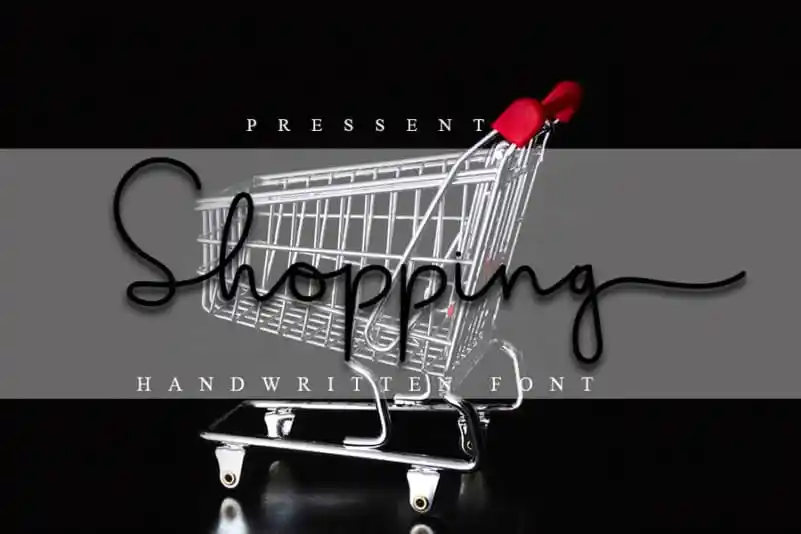
Shopping Script Font – Download Grátis
A Shopping Script Font é uma elegante escolha para quem procura um estilo handwritten contemporâneo e vivaz. Embora mantenha influências tradicionais da escrita aquarelada, essa fonte se destaca pela sua versatilidade em adaptar-se de maneira suave a diversos formatos, dos recortes de letras até os selinhos de papel. Suas características fluidas e dinâmicas são perfeitas para designers que buscam adicionar uma personalização única aos seus trabalhos gráficos, seja no design de cartões de boletim ou na criação de materiais de escritório, estaçãoaria. Uma fonte desta qualidade é um verdadeiro tesouro para qualquer designer à procura de elementos distintos e intrigantes para seus projetos.